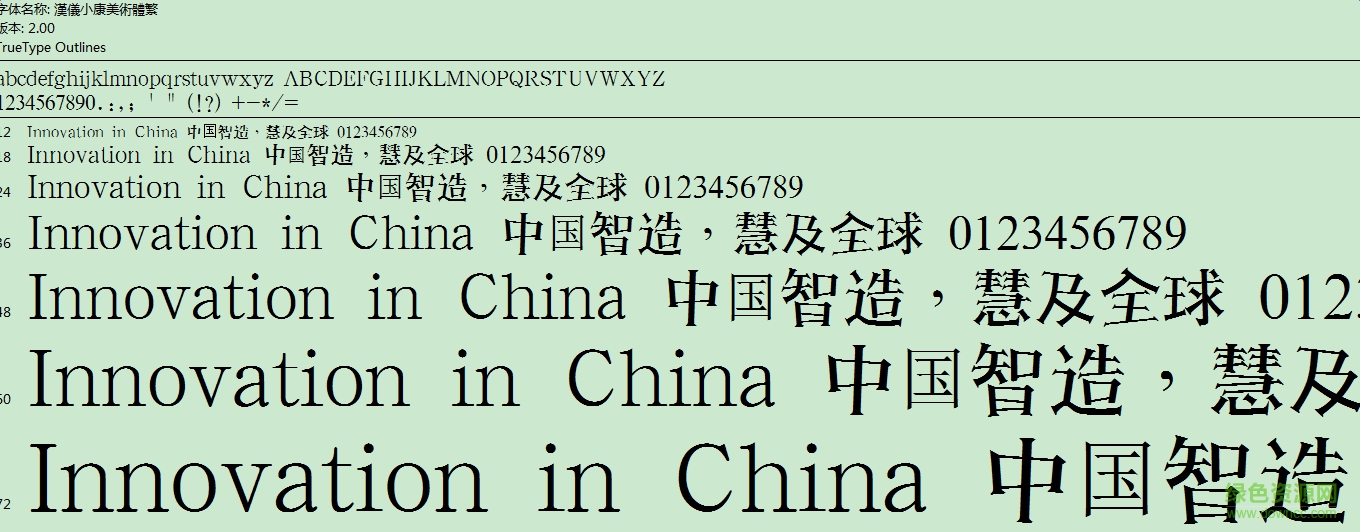
漢儀小康美術(shù)體繁字體是一款漢儀出品的繁體字體,字形美觀有趣,美工設(shè)計(jì)、海報(bào)設(shè)計(jì)等方面都可以使用,有需要的朋友不要錯(cuò)過了,歡迎大家來綠色資源網(wǎng)踴躍下載哦!
漢儀小康美術(shù)體繁,需要在設(shè)計(jì)、排版等方面用到繁體字體的朋友不要錯(cuò)過,字形非常有趣,功能性較強(qiáng)。